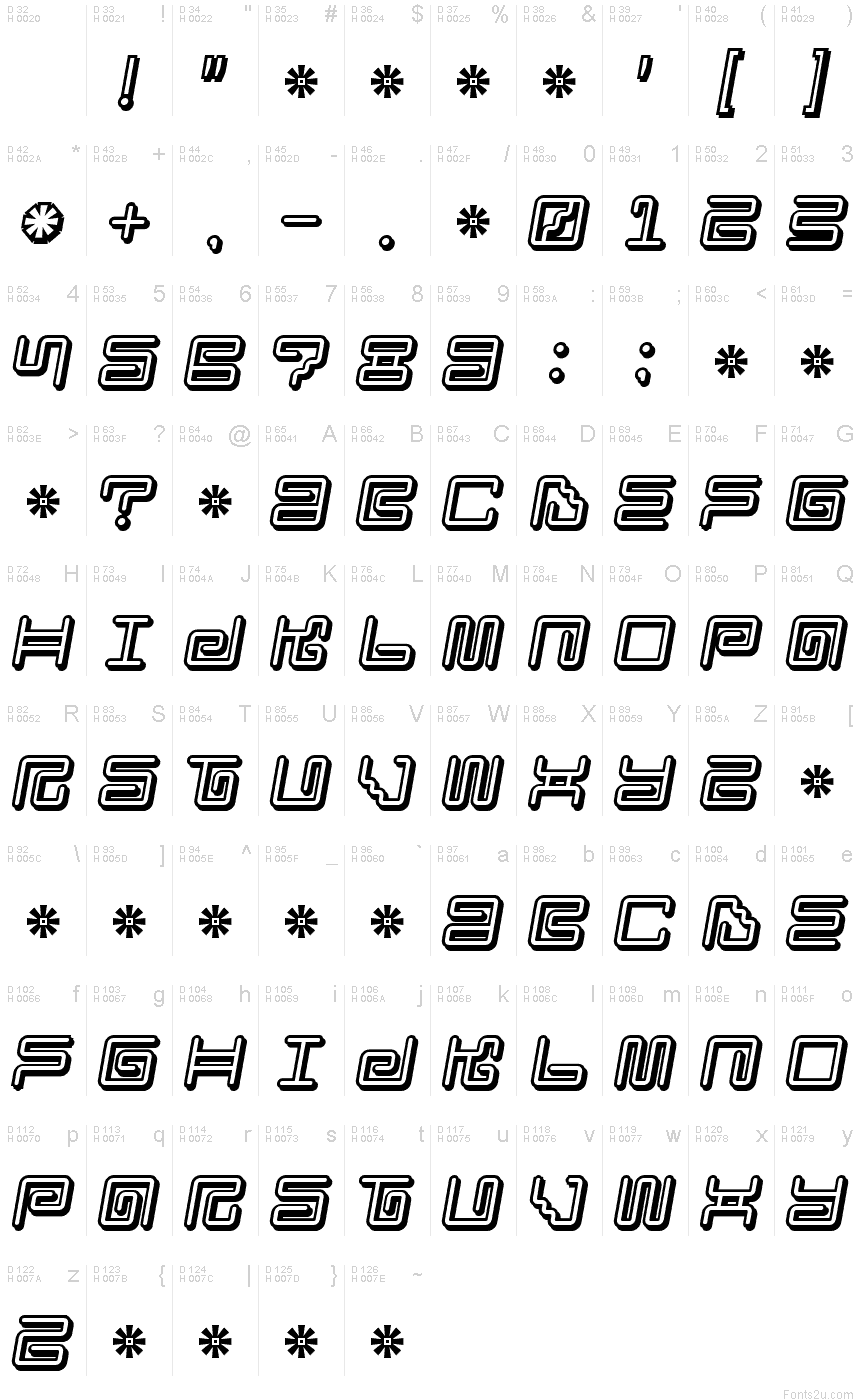
Iron Lounge Smart 2
Iron Lounge Smart 2 di Jakob Fischer è un carattere display gratuito, groovy e futuristico. Le sue lettere si intrecciano come un tubo cromato continuo, con angoli smussati, contorni decisi e un'elegante linea interna che evoca il mix tra un'insegna al neon e un cabinato arcade rétro. Il risultato è un ritmo serrato e vivace che cattura subito lo sguardo e conferisce a ogni parola una presenza forte e cinetica.
Usa Iron Lounge Smart 2 per dare grinta a poster di fantascienza rétro, flyer musicali e da club, loghi di videogiochi, copertine di album techno, adesivi e grafiche social d'impatto. Questo font gratuito brilla se impostato in grande, quindi lascialo dominare il titolo e abbinalo a un carattere sans serif geometrico e pulito per i testi secondari.